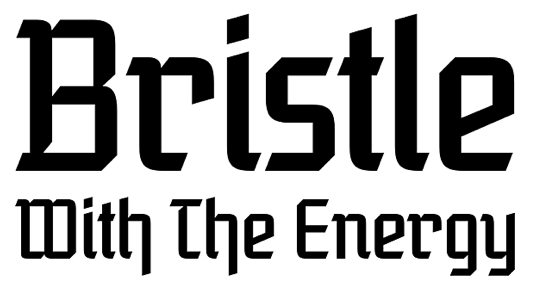
Welche Schrift ist das? Blackletter
Schöne Schrift, weiß ich leider auch nicht. Aber ein Bildchen hab ich für dich:
Wenn ihr noch ein paar Ideen für moderne Blackletter umsetzungen habt, immer her damit
moderne blackletter umsetzungen, interessantes thema.
die frage ist nur immer wo macht man einen schnitt.
in deinem beispiel sieht man ja das die gestaltung da auch viel ausmacht.
eine blaktur wirkt auf den ersten blick nicht zeitgemäß, aber je nach
einsatz und umfeld kann man da noch viel rausholen.
Fakir, Moyenage, Amherst, Birdy, Fraktendon, Blaktur
Blackhaus ist eine schöne moderne …
Ich verweise mal schamlos auf meinen ersten unausgereiften Gehversuch, vielleicht nützt er ja trotz aller Mängel was.
Was das Hilliard’s-Logo betrifft, so würde ich rein intuitiv vermuten, dass die Schrift nur für dieses gemacht wurde, da sich einige Gestaltungsparadigmata nicht schön auf andere Buchstaben übertragen lassen (z. B. f) und die Buchstaben in einer anderen Reihenfolge unschön aussehen könnten, z. B. dürfte die Lücke zwischen r und i recht groß wirken. Alles aber wie gesagt nur eine Vermutung.
Die Vorlage für die Blackhaus war übrigens die
Kursachsen von Peterpaul Weiß, Schriftguß AG, Dresden, 1937
Schriftmuster der »Kursachsen Auszeichnung«,
1937 von Peterpaul Weiß für die Schriftguß AG, Dresden,
entworfen. Hier wird die Abstraktion einzelner Zeichenformen
förmlich auf die Spitze getrieben. Anklänge an die Bauhaus-
Tradition sind kaum zu übersehen